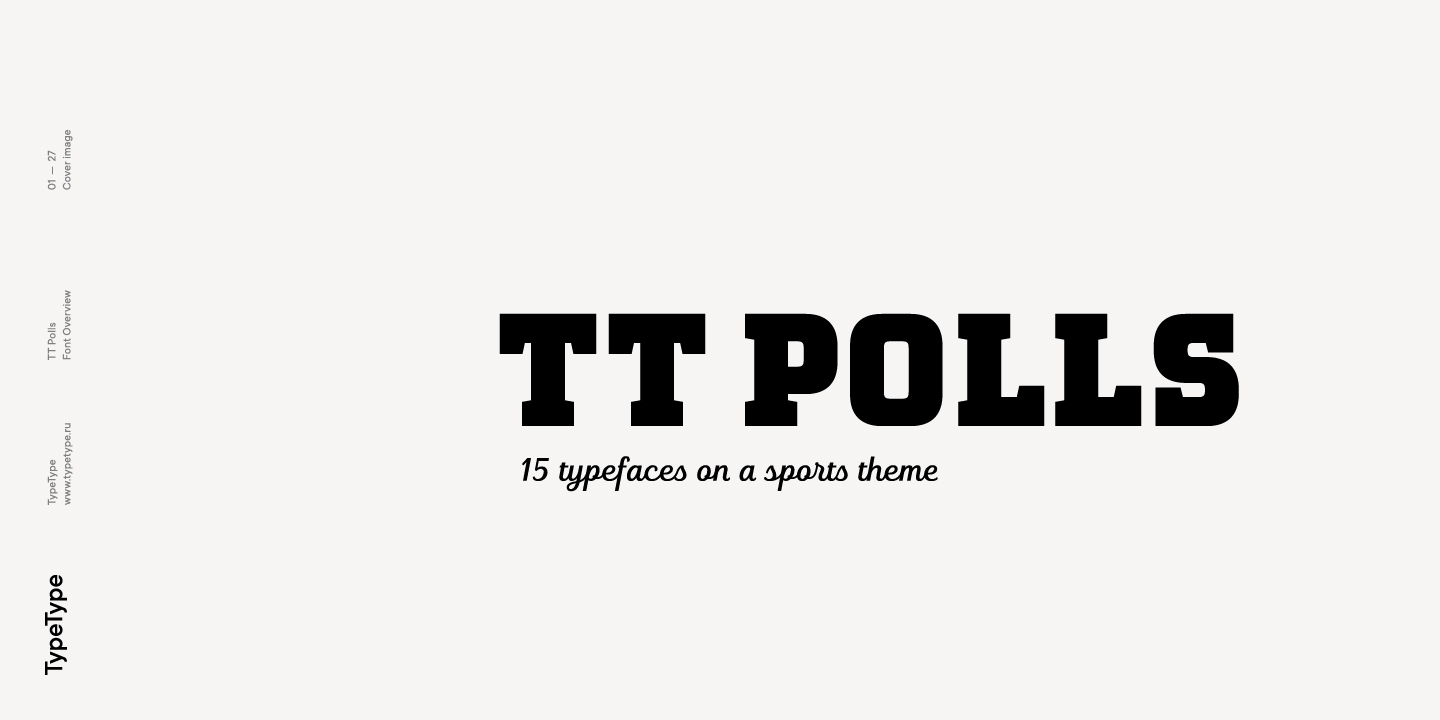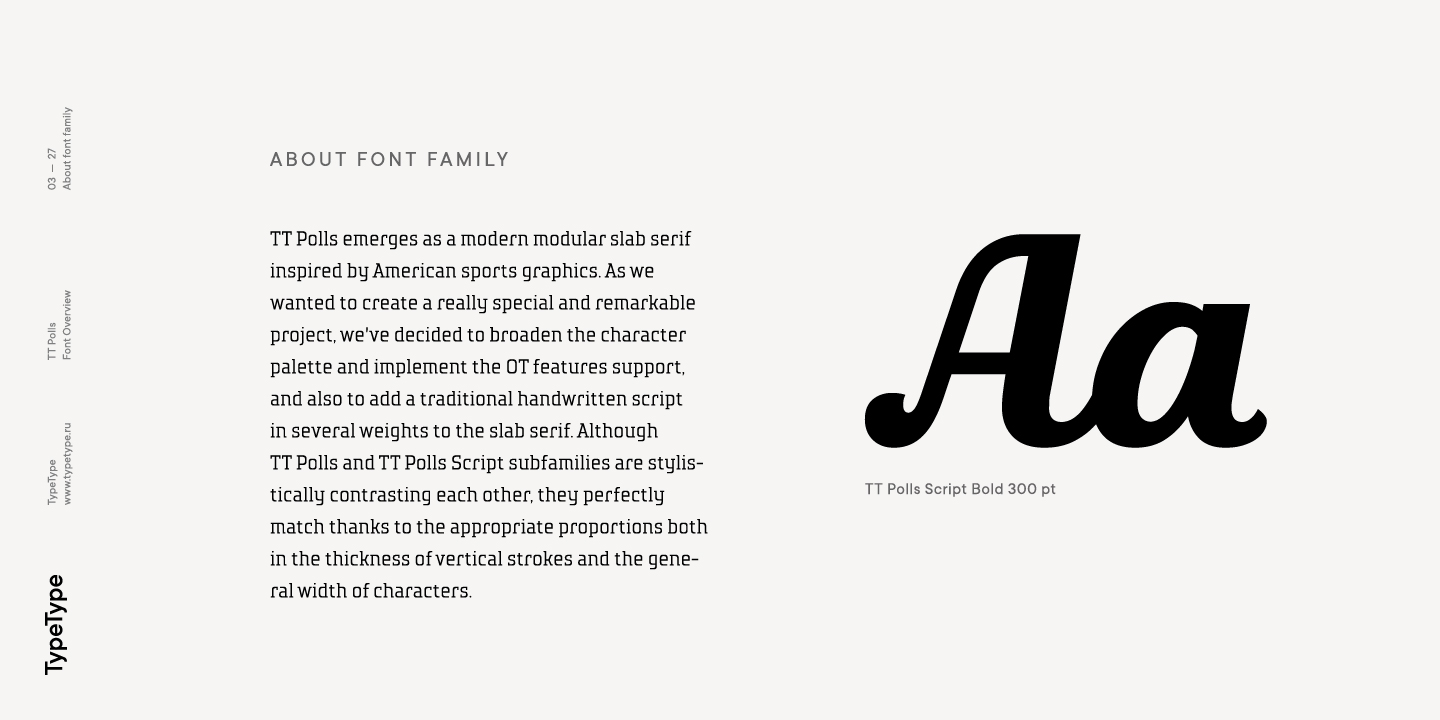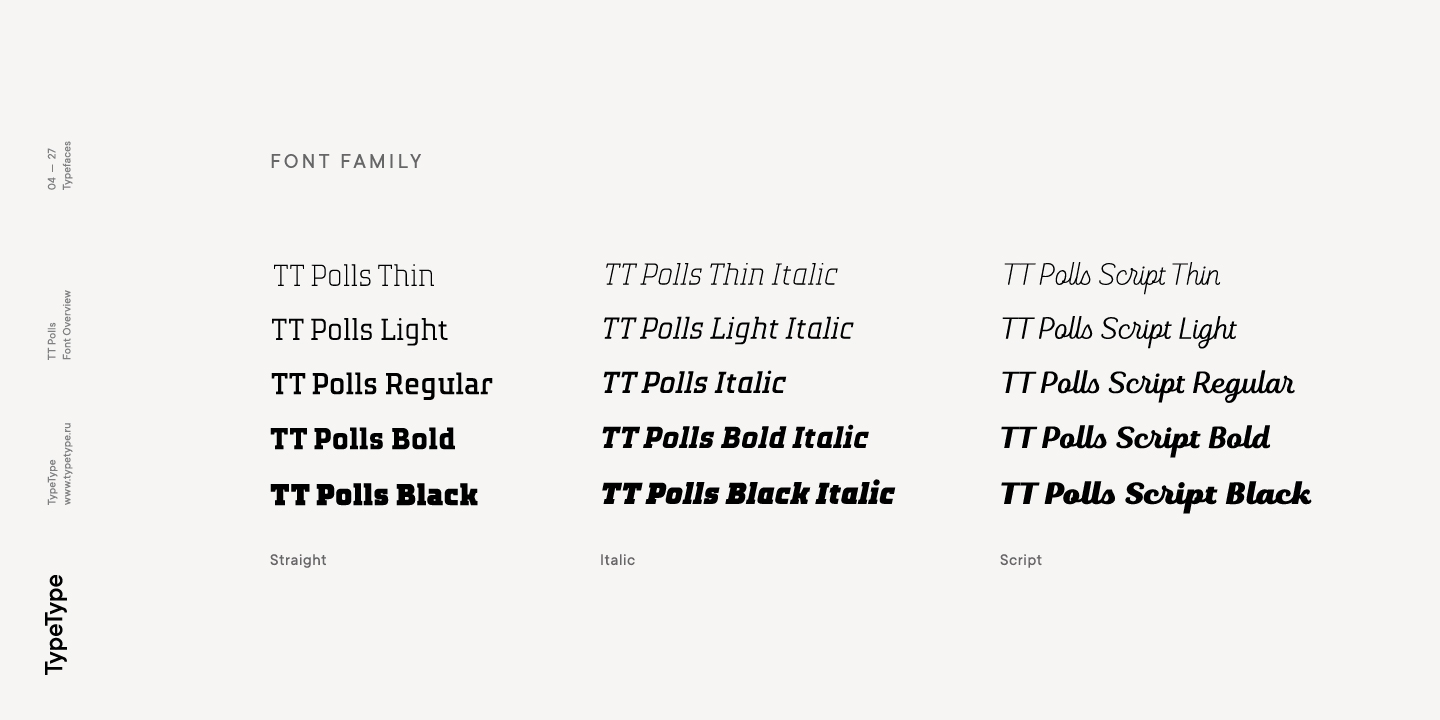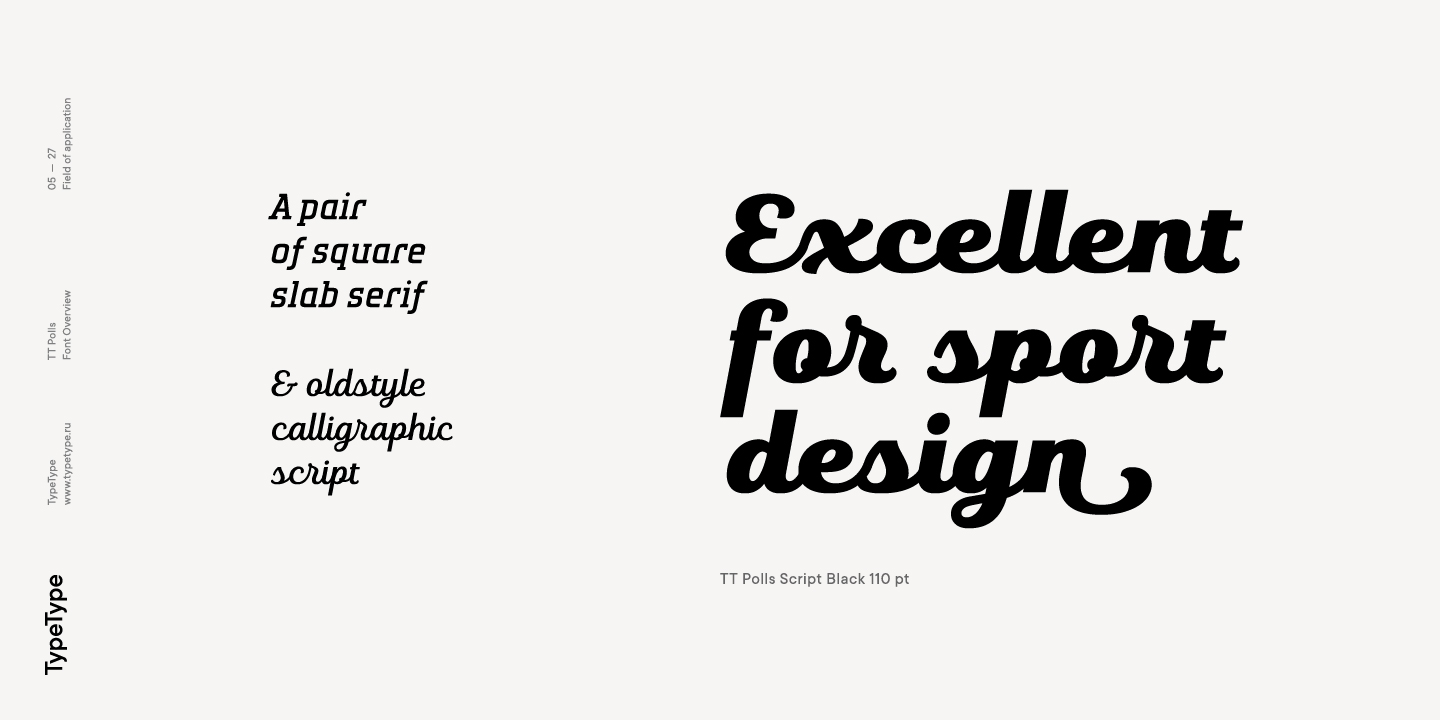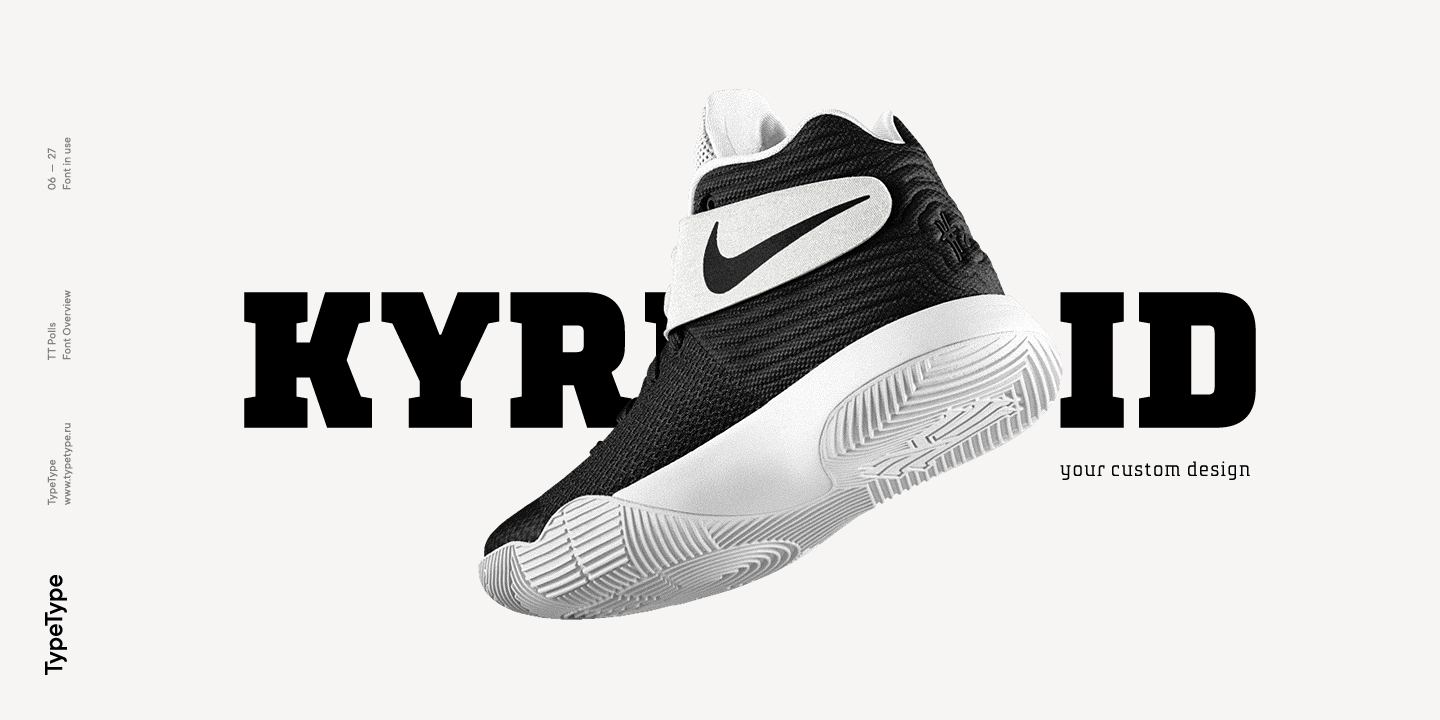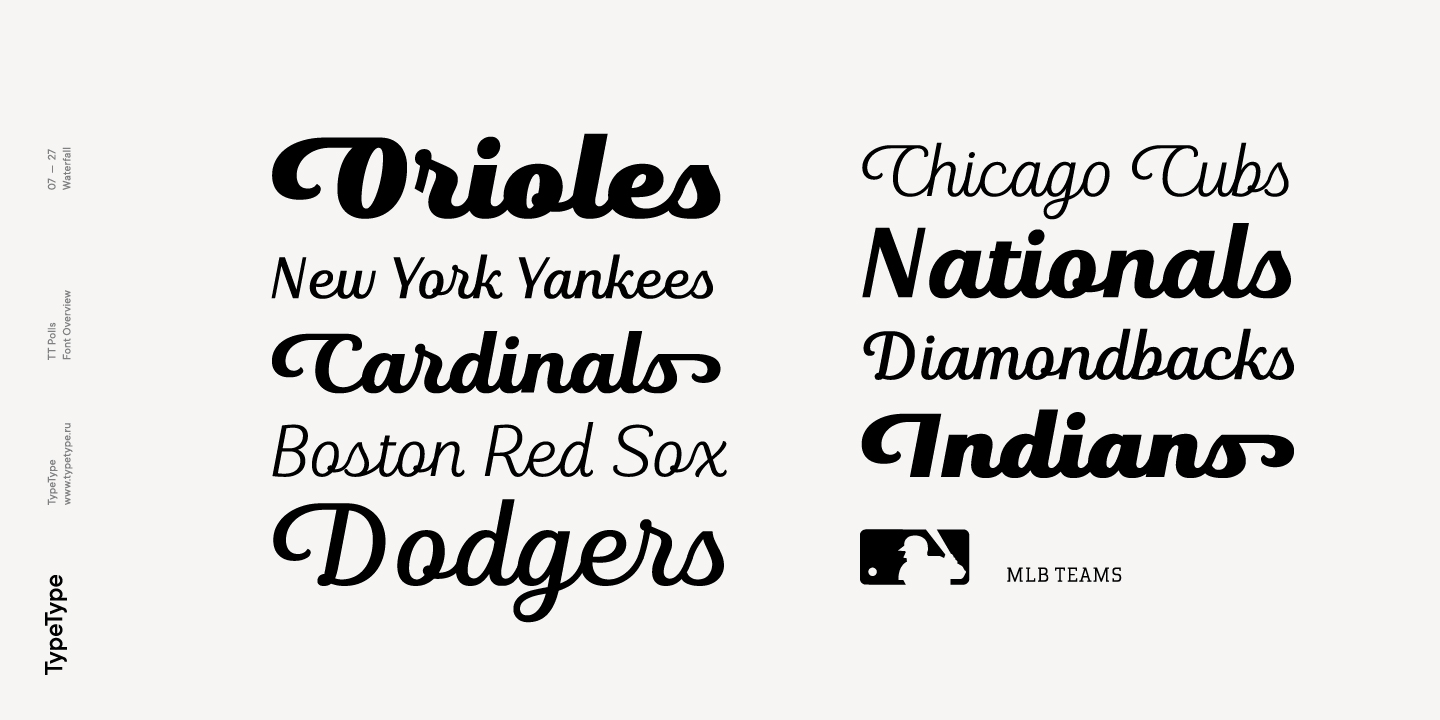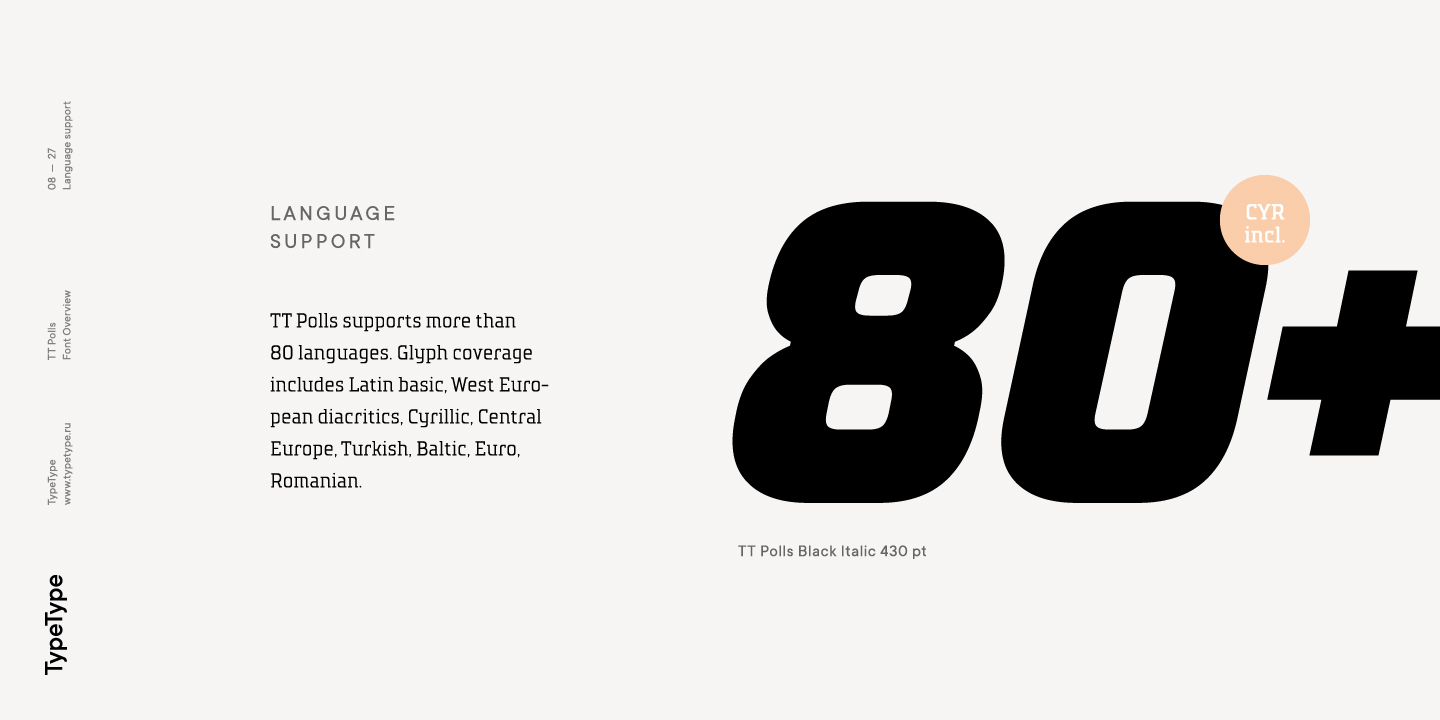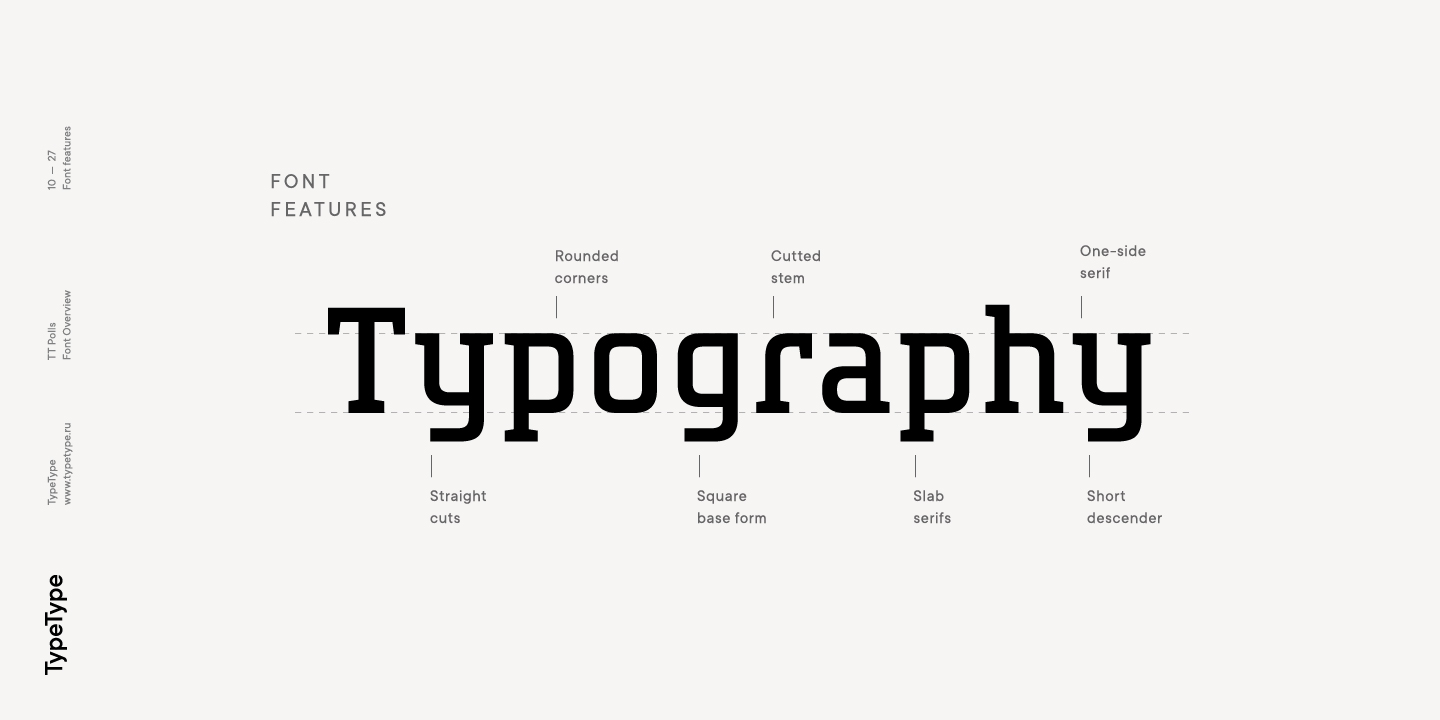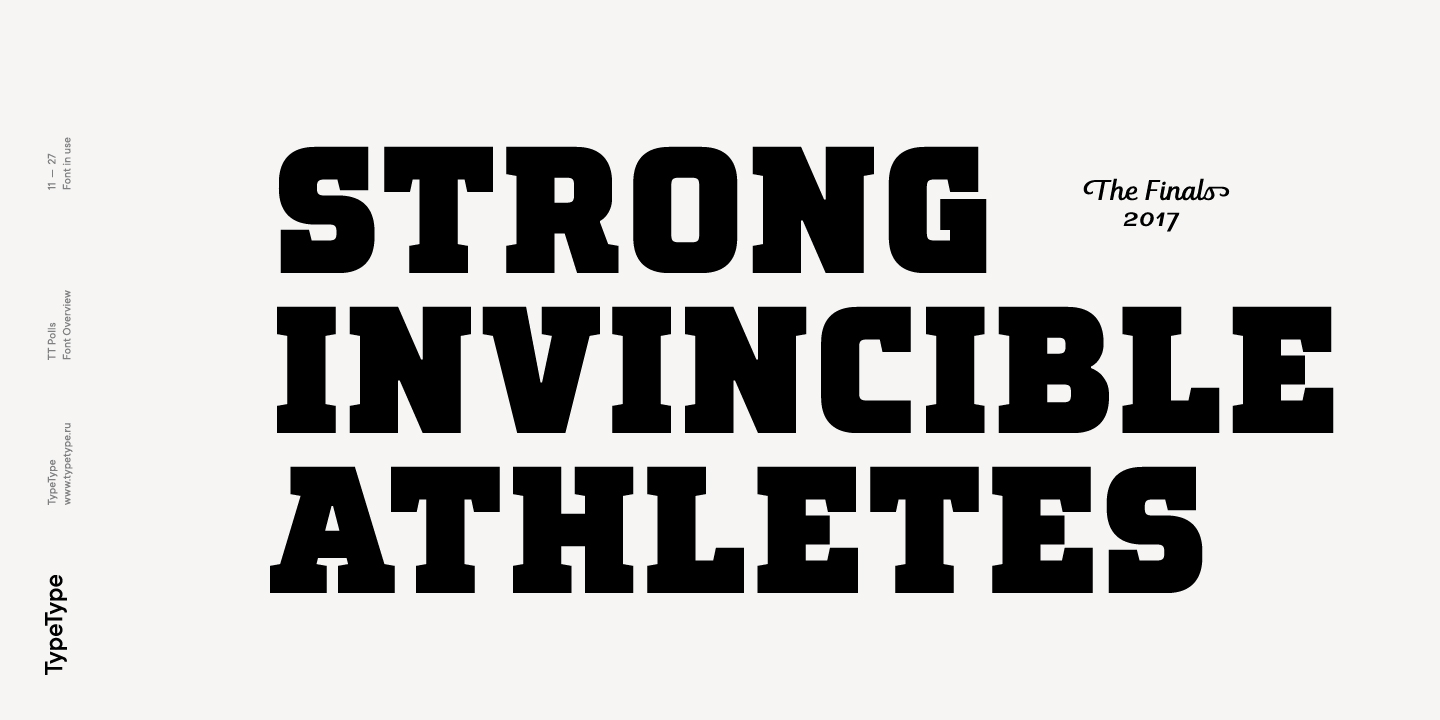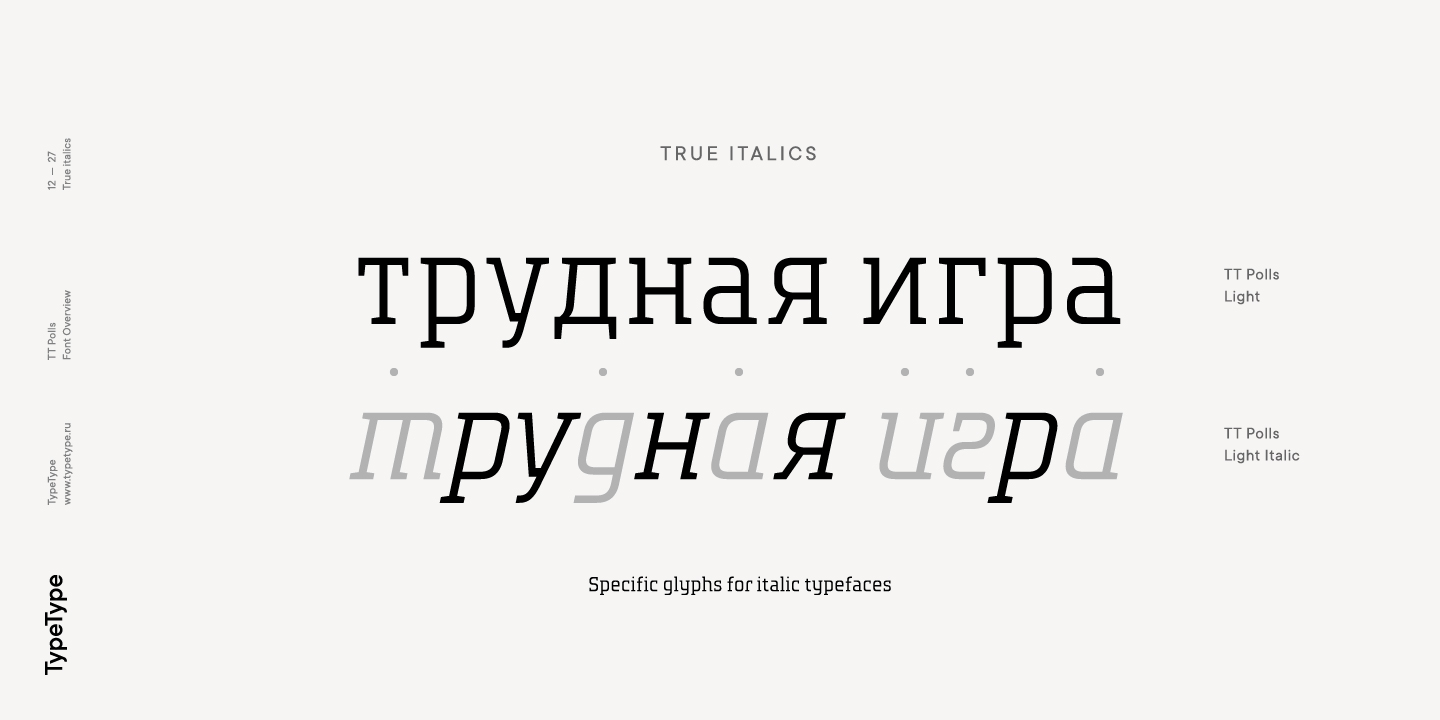
TT Polls
TT Polls — عائلة خطوط مستوحاة من الرسومات الرياضية الأمريكية. تتكوّن من خط سلات سيريف معياري وخط سكريبت تقليدي.
A modern modular slab serif
As we wanted to create a really special and remarkable project, we’ve decided to broaden the character palette and implement the OT features support, and also to add a traditional handwritten script in several weights to the slab serif. Although TT Polls and TT Polls Script subfamilies are stylistically contrasting each other, they perfectly match thanks to the appropriate proportions both in the thickness of vertical strokes and the general width of characters.
TT Polls inspired by American sports graphics, but it is also a great fit to a casual design and application spheres
TT Polls subfamily consists of 5 weights and 5 italics
حول عائلة الخط TT Polls
TT Polls هو مجموعة خطوط بدأت كخط عصري ذو كتل مربعة، مستوحاة من الرسوم البيانية الرياضية الأمريكية. رغبةً في إنشاء مشروع فريد ولا يُنسى، قررنا توسيع مجموعة الرموز وإضافة دعم لميزات OpenType، بالإضافة إلى دمج خط يدوي تقليدي في عدة أوزان.
على الرغم من أن العائلات الفرعية TT Polls وTT Polls Script تتباين في الأسلوب، إلا أن توافق نسبهما، سواء في سمك الخطوط الرأسية أو العرض العام للرموز، يجعلها تتناغم بشكل ممتاز معاً.
تتكون العائلة الفرعية TT Polls من 5 أوزان و5 مائل. أضفنا إليها مجموعة من الربطيات ودعماً واسعاً لميزات OpenType: calt، salt، liga، case، frac، sinf، sups، dnom، numr، tnum. بفضل استخدام البدائل الأسلوبية، يمكن تغيير طابع الخط بشكل كبير، مما يجعله أكثر تكنولوجياً.
على الرغم من أننا صممنا مجموعة TT Polls مع وضع التصميم الرياضي في الاعتبار، سواء كانت الكتابات على قمصان لاعبي البيسبول أو الأرقام على جوانب السيارات الرياضية، إلا أن النسخة النهائية من TT Polls تناسب أيضاً التصاميم الأكثر غير رسمية والمجالات الأخرى.
ميزات OpenType
TT Polls Script
salt | Stylistic Alternates
agly
liga | Standard Ligatures
ffi fj
case | Case Sensitive Forms
({[H]})
dlig | Discretionary Ligatures
st sp
swsh | Swashes
a b g
liga | Standard Ligatures
fb ff
case | Case Sensitive Forms
({[H]})
numr | Numerators
H123